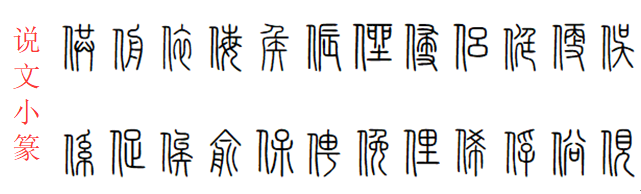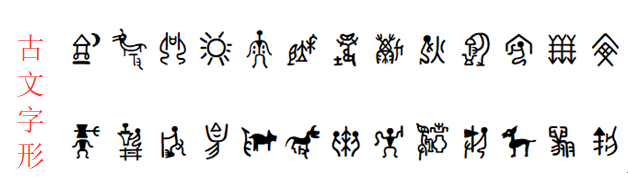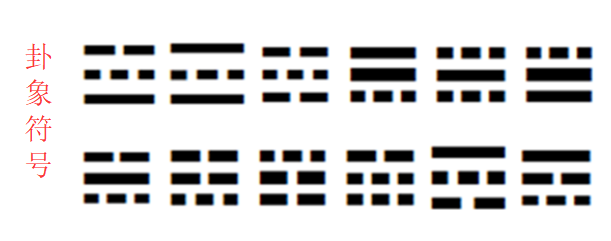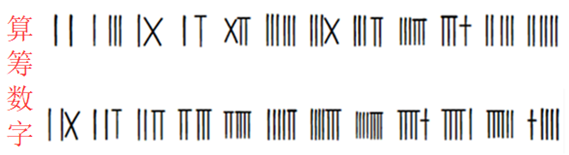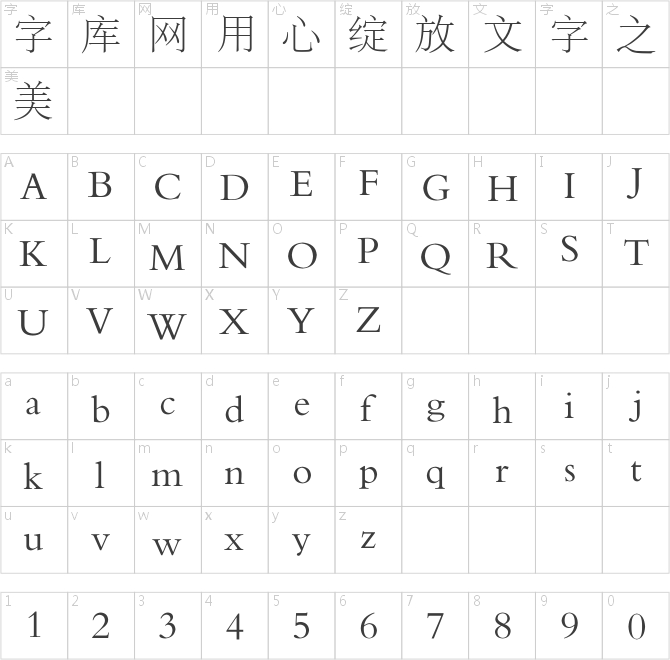
字體名稱: 中華書局宋體
作者版權: 方正/古聯
中華書局宋體
中華書局宋體字庫是中華書局古聯公司為滿足古籍和文史哲學術論著數字化建設的需要,委托北大方正公司制作的字庫。
基本情況
字庫由“中華書局宋體00平面”、“中華書局宋體02平面”和“中華書局宋體15平面”三個ttf字體文件組成,收字已超過13萬。其中“中華書局宋體00平面”、“中華書局宋體02平面”字體中的字符授權自“方正宋體超大字符集”,支持基本通用字符及所有CJK漢字;“中華書局宋體15平面”為古聯公司委托方正公司制作的專用字符集,收錄Unicode未定義的楷書漢字、古文及古代文化符號。
字庫特色
1. 字體收錄的漢字多,不僅涵蓋了Unicode12.0的所有已定義CJK漢字,還有超過2萬制作時Unicode未定義的出自古籍的漢字字符,而且隨著古籍數字化工作的進行,漢字字符還會增加。
2. 字體覆蓋范圍廣,不僅有宋體風格的楷書漢字,還有全部說文小篆、卦象符號、算籌數字、注音字母、國際音標符號等,也包含了大部分的拉丁文、日文、希臘文等外文字符。
3. 字庫建設過程中,以Unicode發布的字符集為標準。漢字部分盡量快速響應Unicode關于CJK字符集的更新,專用區造字通過多屬性標注、多屬性查重,盡量避免產生重復造字;其他區塊的字符則視數字化工作的需要,陸續添加。
說明:
1. Unicode中的兼容區一般被視為未定義、非標準、被廢棄的區塊。如中日韓兼容表意文字區(CJK Compatibility Ideographs),編碼范圍為F900–FAFF,這一部分的字符一般在CJK漢字中被定義,無需重復收錄。
2. 擴展注音符號、中日韓筆劃、中日韓兼容、中日韓標點符號和帶圈或括弧中日韓字母及月份這幾個與中文相關的區塊的字符,在古籍和文史哲學術論著數字化中利用率較低,暫未整批收錄。